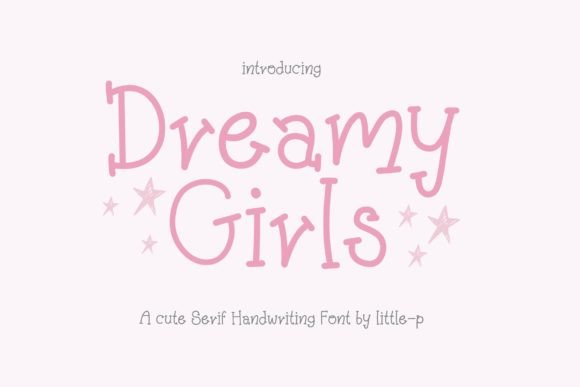
Dreamy Girls
Die richtigen Designelemente zu finden, kann eine Herausforderung sein, aber Dreamy Girls bietet eine außergewöhnliche Sammlung, die Ihre Arbeit sofort aufwertet.
Egal, ob Sie POD-Produkte (Print on Demand), Hochzeitseinladungen oder Social-Media-Grafiken erstellen, Dreamy Girls ist die ideale Wahl.